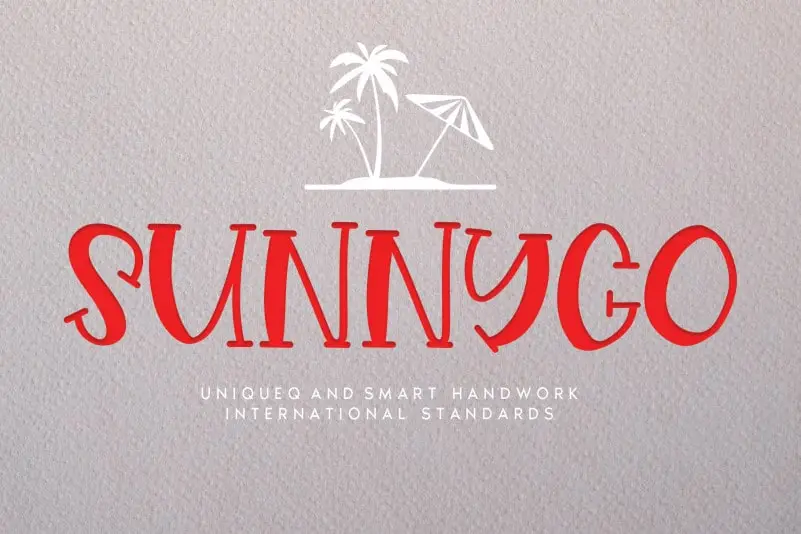
Sunnygo Display Font é uma fonte de exibição divertida e despretensiosa que traz vida a qualquer design. Seja para criar cartões personalizados ou até mesmo banners publicitários, essa elegante fonte adiciona um toque encantador ao seu trabalho, tornando-o ainda mais chamativo e memorável. Suas linhas arredondadas e desenhos únicos garantem que você sempre tenha uma solução criativa para seus projetos, seja para criar cartões de presente personalizados ou banners publicitários. Inclua Sunnygo Display Font em suas próximas ideias criativas e perceba como ela os faz sobressair.